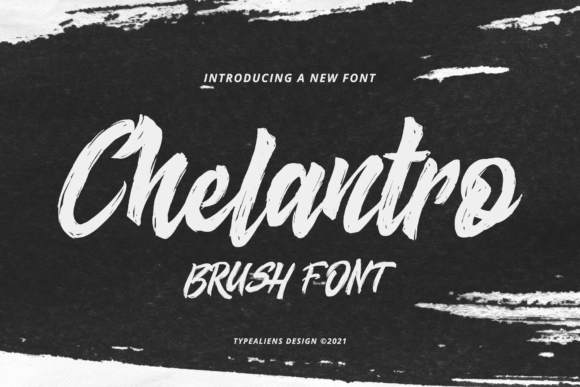
[Creativefabrica] Chelantro Font (2021)
Chelantro - это крутой, смелый и матовый дисплейный шрифт.
Его можно легко подобрать к невероятно большому набору проектов, поэтому добавьте его в свои творческие идеи и обратите внимание, как он выделяет их!